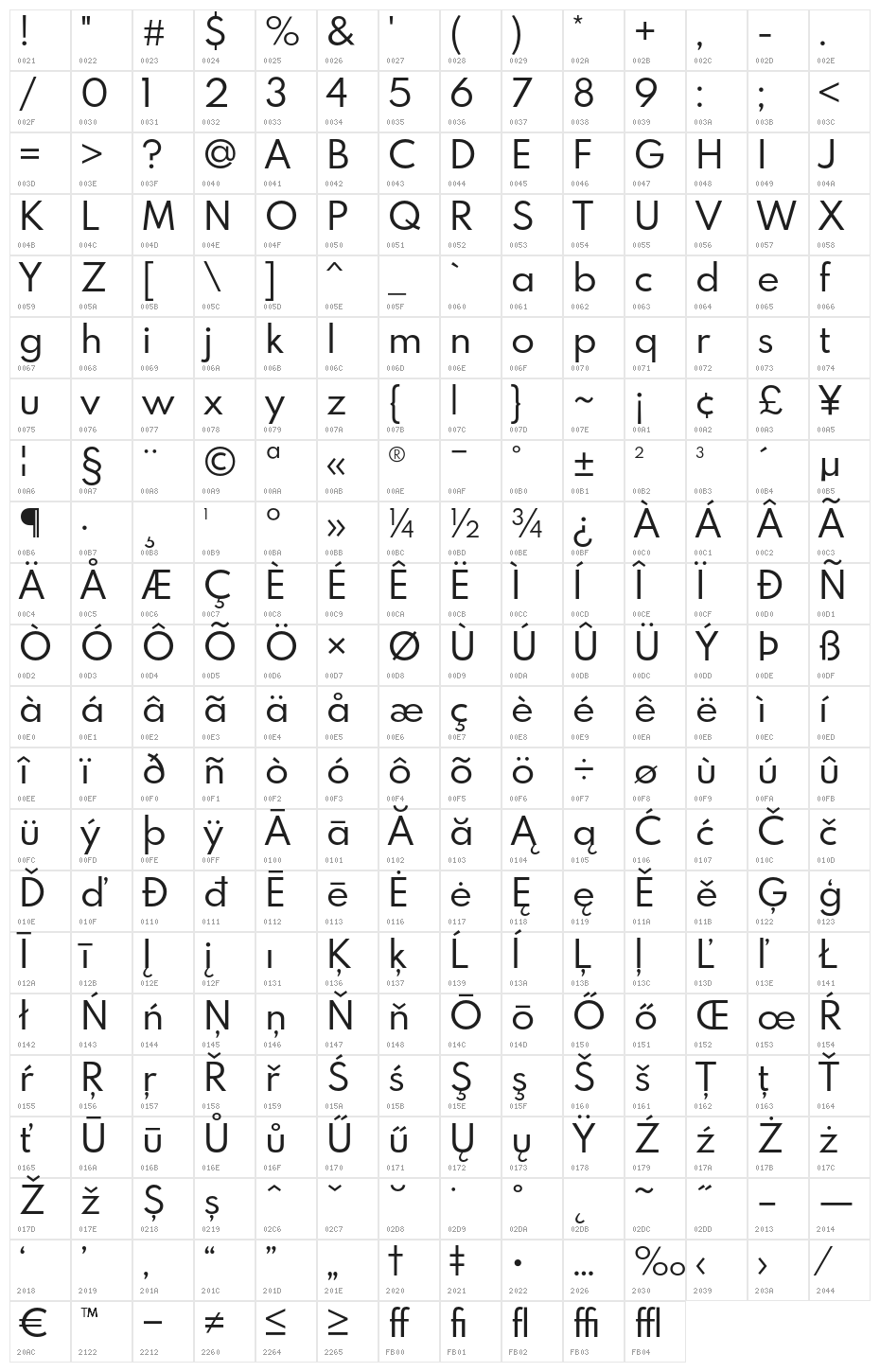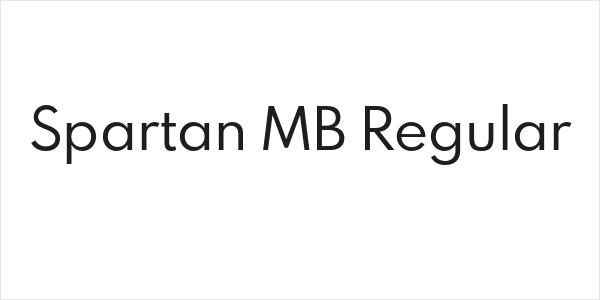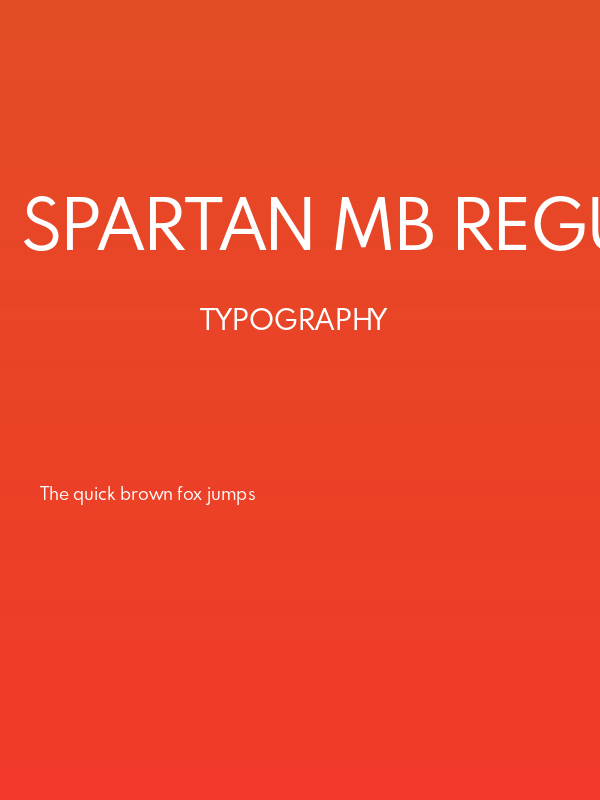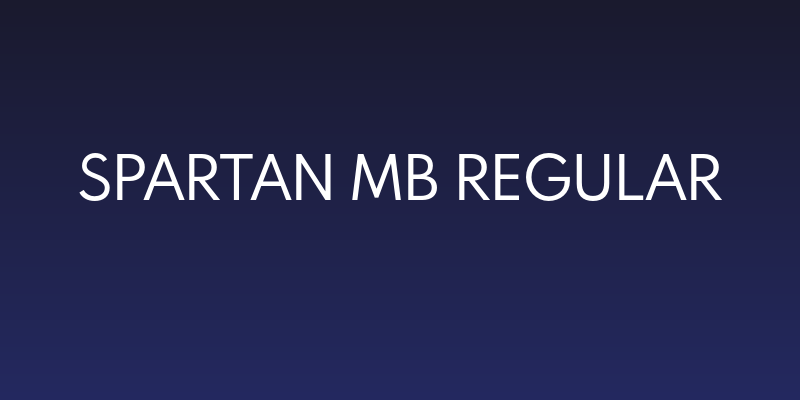
Spartan MB Regular Font
✎ Sans Serif
| حالة الاستخدام | Headlines, Body text, Logos |
| مشاريع مقترحة | Ideal for branding, web design, advertising, and editorial layouts where clarity and modernity are essential. |